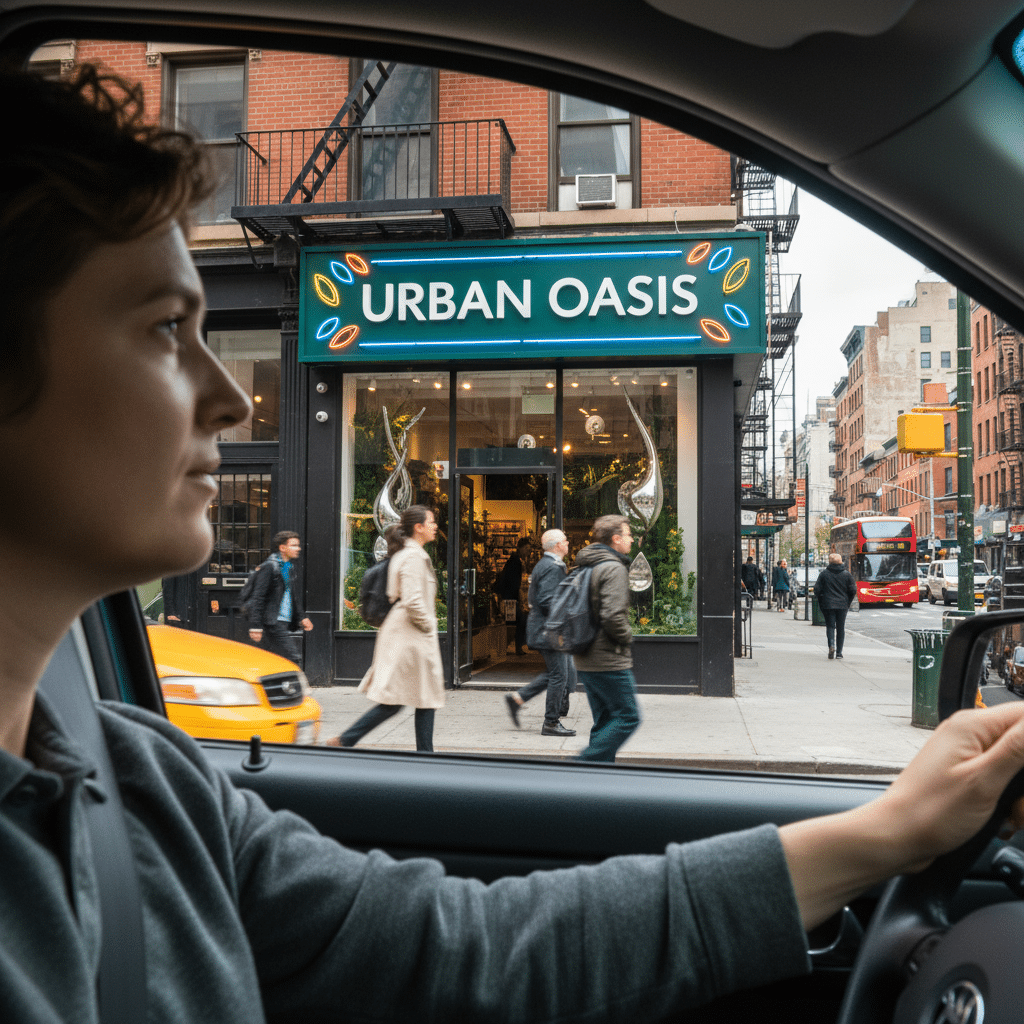
อ่านยาก=ลูกค้าหนี! เทคนิคเลือก ‘ฟอนต์ทำป้าย’ ให้อ่านง่ายใน 3 วิ แม้ขับรถผ่านไวๆ
การออกแบบป้ายหน้าร้านหรือป้ายโฆษณาริมทางให้ประสบความสำเร็จนั้นมีองค์ประกอบหลายอย่าง แต่ปัจจัยที่มักถูกมองข้ามแต่กลับมีความสำคัญอย่างยิ่งคือการเลือกใช้ “ฟอนต์” ตัวอักษรที่ไม่เหมาะสมอาจทำให้ข้อความที่ต้องการสื่อสารถูกบดบัง อ่านยาก และส่งผลให้ลูกค้าเป้าหมายไม่สามารถรับรู้ข้อมูลได้ทันในเวลาอันสั้น
ประเด็นสำคัญที่ต้องพิจารณาในการเลือกฟอนต์ทำป้าย
- ความชัดเจนมาก่อนความสวยงาม: เลือกฟอนต์ที่มีรูปทรงตัวอักษรชัดเจน โดยเฉพาะฟอนต์ภาษาไทยแบบมีหัว ซึ่งช่วยให้แยกแยะพยัญชนะที่คล้ายกันได้ง่าย หลีกเลี่ยงฟอนต์ลายมือหรือฟอนต์ที่มีการตกแต่งมากเกินไป
- ขนาดและระยะห่างต้องเหมาะสม: ขนาดของฟอนต์ต้องสัมพันธ์กับระยะการมองเห็นของกลุ่มเป้าหมาย ป้ายริมถนนที่ผู้คนขับรถผ่านต้องใช้ตัวอักษรขนาดใหญ่กว่าป้ายหน้าร้านทั่วไป นอกจากนี้ การเว้นระยะห่างระหว่างตัวอักษร (Kerning) ที่พอดีจะช่วยให้ข้อความไม่ติดกันเป็นพืด
- ความเปรียบต่างของสี (Contrast) คือหัวใจ: สีของตัวอักษรต้องตัดกับสีพื้นหลังอย่างชัดเจน คู่สีที่ให้คอนทราสต์สูง เช่น ตัวอักษรสีดำบนพื้นหลังสีขาวหรือสีเหลือง จะช่วยให้มองเห็นได้ง่ายจากระยะไกล
- ความสม่ำเสมอคือการสร้างแบรนด์: การใช้ฟอนต์เพียงตระกูลเดียว (Font Family) ในการออกแบบป้ายจะช่วยสร้างเอกลักษณ์ที่น่าจดจำและเสริมสร้างความเป็นมืออาชีพให้กับแบรนด์
บทความนี้จะสำรวจเทคนิคและหลักการสำคัญในการเลือก อ่านยาก=ลูกค้าหนี! เทคนิคเลือก ‘ฟอนต์ทำป้าย’ ให้อ่านง่ายใน 3 วิ แม้ขับรถผ่านไวๆ ซึ่งเป็นองค์ประกอบสำคัญที่ผู้ประกอบการและนักออกแบบไม่ควรมองข้าม การเลือกฟอนต์ที่เหมาะสมไม่เพียงแต่ช่วยให้การสื่อสารมีประสิทธิภาพสูงสุด แต่ยังเป็นก้าวแรกในการสร้างการรับรู้และดึงดูดลูกค้าให้เข้ามายังธุรกิจอีกด้วย การทำความเข้าใจในศาสตร์แห่งการใช้ตัวอักษร (Typography) จะเปลี่ยนป้ายธรรมดาให้กลายเป็นเครื่องมือทางการตลาดที่ทรงพลังได้อย่างไม่น่าเชื่อ
ทำไมการเลือกฟอนต์ทำป้ายจึงส่งผลกระทบโดยตรงต่อธุรกิจ
ในยุคที่การแข่งขันทางธุรกิจทวีความรุนแรง ป้ายหน้าร้านและป้ายโฆษณาไม่ได้เป็นเพียงเครื่องหมายบอกตำแหน่งที่ตั้งอีกต่อไป แต่เป็นเครื่องมือสื่อสารด่านแรกที่สร้างปฏิสัมพันธ์กับลูกค้าเป้าหมาย การเลือกใช้ฟอนต์จึงเปรียบเสมือนการเลือก “น้ำเสียง” ให้กับแบรนด์ ซึ่งสามารถสร้างหรือทำลายโอกาสทางธุรกิจได้ในเสี้ยววินาที
การสร้างความประทับใจแรกเห็นในเสี้ยววินาที
สำหรับผู้ที่ขับรถผ่านหรือเดินผ่านหน้าร้าน พวกเขามีเวลาเพียงไม่กี่วินาทีในการกวาดสายตามองและตัดสินใจว่าธุรกิจนั้นน่าสนใจหรือไม่ ฟอนต์ที่อ่านง่ายและดูเป็นมืออาชีพจะสร้างความน่าเชื่อถือและความประทับใจในเชิงบวกได้ทันที ในทางกลับกัน ฟอนต์ที่ซับซ้อน อ่านยาก หรือดูไม่สวยงาม อาจทำให้เกิดความรู้สึกสับสน ไม่เป็นระเบียบ และลดทอนภาพลักษณ์ของแบรนด์ลงไปอย่างน่าเสียดาย การลงทุนเวลาเพื่อเลือกฟอนต์ที่เหมาะสมจึงเป็นการลงทุนเพื่อสร้างความประทับใจแรกที่แข็งแกร่งและยั่งยืน
การสื่อสารข้อมูลสำคัญอย่างรวดเร็วและแม่นยำ
วัตถุประสงค์หลักของป้ายคือการสื่อสารข้อมูล ไม่ว่าจะเป็นชื่อร้าน ประเภทสินค้า โปรโมชั่น หรือข้อมูลติดต่อ หากฟอนต์ที่ใช้นั้นอ่านยาก ผู้รับสารอาจเข้าใจข้อมูลผิดพลาดหรือไม่สามารถอ่านได้ทันเวลา โดยเฉพาะป้ายริมถนนที่ต้องการการรับรู้ในระยะเวลาอันสั้น การเลือกฟอนต์ที่ชัดเจนและเรียบง่ายจึงเป็นสิ่งจำเป็นเพื่อให้แน่ใจว่าข้อความสำคัญถูกส่งไปถึงกลุ่มเป้าหมายได้อย่างครบถ้วนและแม่นยำ ซึ่งจะนำไปสู่การจดจำแบรนด์และเพิ่มโอกาสในการขายได้ในที่สุด
หลักการพื้นฐานของ Typography สำหรับออกแบบป้ายโฆษณา
Typography หรือศาสตร์แห่งการออกแบบและจัดวางตัวอักษร เป็นมากกว่าแค่การเลือกฟอนต์สวยๆ แต่เป็นกระบวนการที่ต้องคำนึงถึงจิตวิทยาการรับรู้ของมนุษย์เพื่อให้การสื่อสารบรรลุผลสูงสุด การทำความเข้าใจหลักการพื้นฐานเหล่านี้จะช่วยให้การออกแบบป้ายมีประสิทธิภาพมากขึ้น
ความชัดเจน (Clarity) และความสามารถในการอ่าน (Readability)
สองคำนี้มักถูกใช้สลับกัน แต่มีความหมายที่แตกต่างกันในเชิงการออกแบบ ความชัดเจน (Clarity หรือ Legibility) หมายถึงความง่ายในการแยกแยะตัวอักษรแต่ละตัวออกจากกัน เช่น การแยกแยะระหว่าง ‘ก’ กับ ‘ถ’ หรือ ‘พ’ กับ ‘ฟ’ ส่วน ความสามารถในการอ่าน (Readability) หมายถึงความง่ายในการอ่านข้อความหรือประโยคที่ต่อเนื่องกันอย่างลื่นไหล
สำหรับป้ายโฆษณา ความชัดเจนมีความสำคัญเป็นอันดับแรก โดยเฉพาะในบริบทภาษาไทย ฟอนต์ที่มีหัว (Looped fonts) มักจะให้ความชัดเจนสูงกว่าฟอนต์ไม่มีหัว (Loopless fonts) เนื่องจากลักษณะของ “หัว” ช่วยให้สมองจดจำและแยกแยะพยัญชนะที่มีรูปทรงคล้ายคลึงกันได้เร็วยิ่งขึ้น เช่น ม/น, อ/ฮ, หรือ ก/ท เป็นต้น ดังนั้น ควรหลีกเลี่ยงฟอนต์ที่มีการตกแต่งซับซ้อน ฟอนต์ลายมือที่หวัดเกินไป หรือฟอนต์ที่มีเส้นบางเฉียบ เพราะจะลดทอนความชัดเจนลงอย่างมาก
น้ำหนักและความหนาของตัวอักษร (Font Weight)
น้ำหนักของฟอนต์หมายถึงความหนาของเส้นตัวอักษร ซึ่งมีตั้งแต่แบบบาง (Light), ปกติ (Regular), ไปจนถึงหนา (Bold) และหนาพิเศษ (Black) การเลือกน้ำหนักที่เหมาะสมมีความสำคัญอย่างยิ่งต่อการมองเห็นในระยะไกล
- ฟอนต์ที่บางเกินไป (Thin/Light): อาจมองไม่เห็นหรือจางหายไปกับพื้นหลังเมื่อมองจากระยะไกล โดยเฉพาะในสภาพแสงที่ไม่เอื้ออำนวย
- ฟอนต์ที่หนาเกินไป (Black/Heavy): อาจทำให้พื้นที่ว่างภายในตัวอักษร (Counter) หายไป ส่งผลให้ตัวอักษรดูกลมติดกันเป็นก้อนและอ่านยาก เช่น ตัว ‘อ’ อาจดูเหมือนวงกลมทึบ